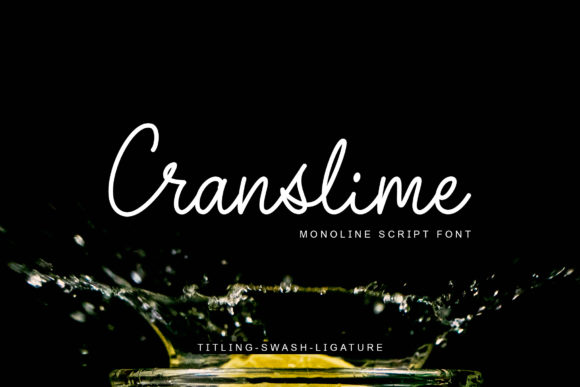
Creativefabrica Cranslime Font
[Creativefabrica] Cranslime Font
Cranslime - это стильный и хорошо сбалансированный шрифт сценария.
Он имеет чистую, тонкую и гладкую вибрацию и станет хитом для любого дизайна, к которому вы захотите его добавить.